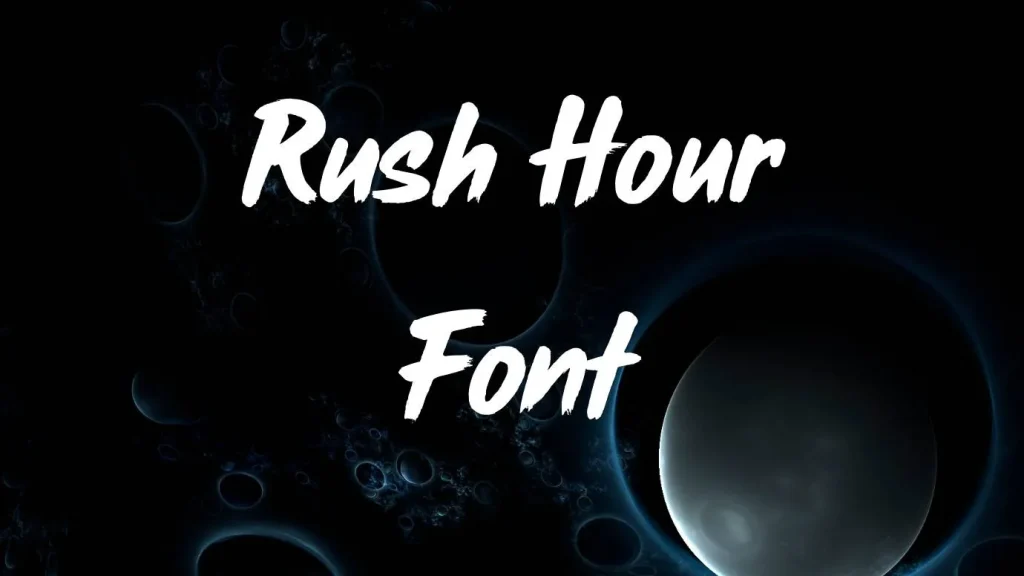
Tác giả: BLKBK
Phân loại: Cá tính
Font SVN Rush Hour thuộc bộ font SNV đây là một font chữ độc đáo, nổi bật với phong cách mạnh mẽ và hiện đại, lý tưởng cho các thiết kế đòi hỏi sự cá tính và sáng tạo. Với các nét chữ đậm, gãy gọn, font này mang lại cảm giác năng động và đầy sức sống, phù hợp cho các dự án liên quan đến quảng cáo, poster, hoặc các ấn phẩm thương mại. Font SVN Rush Hour không chỉ dễ đọc mà còn tạo điểm nhấn mạnh mẽ, giúp thông điệp của bạn nổi bật và thu hút sự chú ý của người xem.